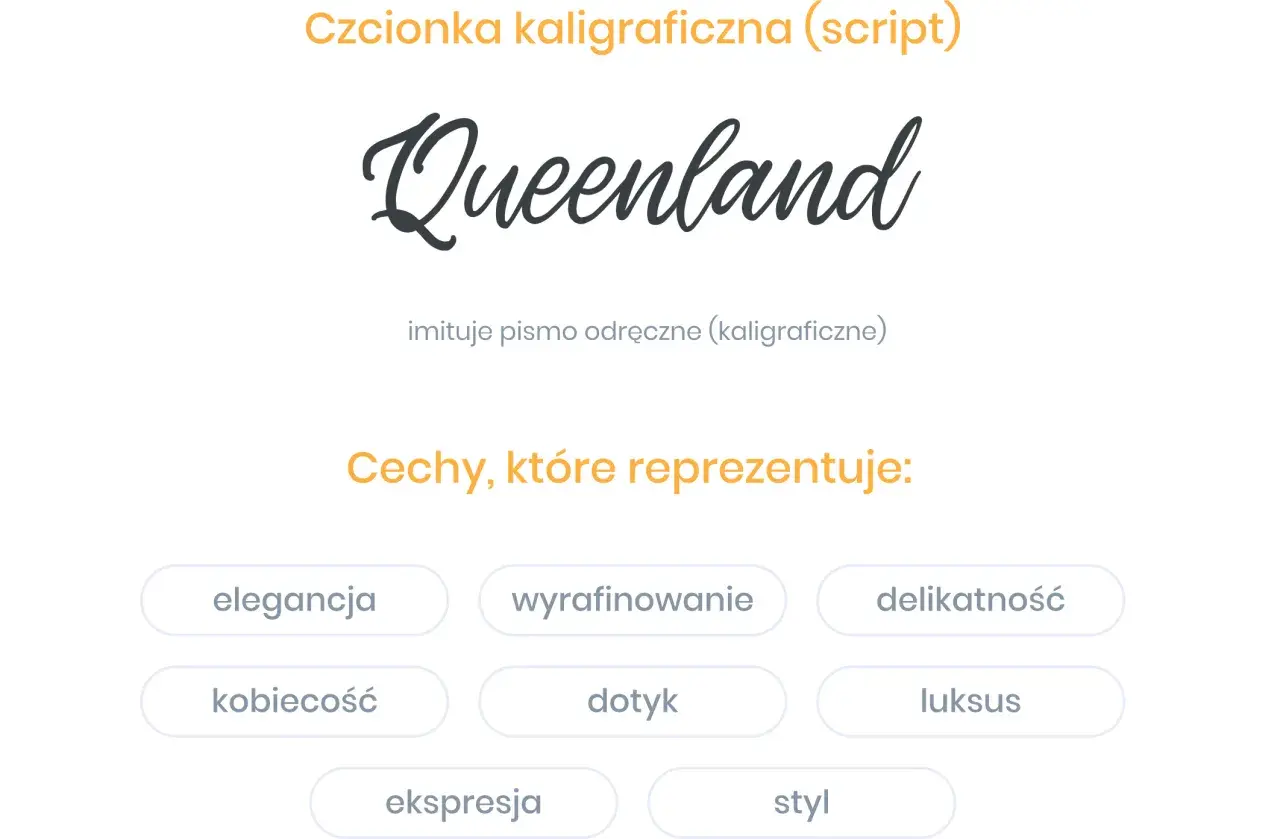
Dobry napis potrafi sprawić, że lokalna marka zostanie zapamiętana po jednym spojrzeniu. Czcionka ozdobna pomaga zbudować klimat reklamy, szyldu, menu czy posta w mediach społecznościowych, ale łatwo przesadzić z dekoracyjnością i stracić czytelność. Pokażę, jakie style warto rozważyć, gdzie sprawdzają się najlepiej i jak wybrać krój, który będzie efektowny także w praktycznym użyciu.
Ozdobny krój działa najlepiej wtedy, gdy wspiera komunikat marki
- Jedna dekoracyjna rodzina zwykle wystarczy w projekcie reklamowym.
- Polskie znaki trzeba sprawdzić przed rozpoczęciem składu.
- Nagłówki i krótkie hasła są lepszym miejscem dla ozdobnych liter niż długie akapity.
- Kontrast, rozmiar i odstępy decydują o czytelności bardziej niż sam styl fontu.
Co wyróżnia dekoracyjne kroje pisma
Font dekoracyjny ma przede wszystkim przyciągać uwagę i budować skojarzenia. Może przypominać pismo odręczne, dawny szyld, elegancką kaligrafię, plakat retro albo liternictwo inspirowane neonami. Nie traktuję go jednak jako zamiennika zwykłego fontu do całej treści. Jego siła polega na tym, że pojawia się w odpowiednim miejscu i w ograniczonej ilości.
W reklamie lokalnej typografia często zastępuje część obrazu. Nazwa kawiarni zapisana miękkim krojem sugeruje kameralność, a ciężkie litery w stylu vintage mogą pasować do burgerowni, barber shopu lub sklepu z odzieżą używaną. To nie jest wyłącznie kwestia estetyki. Krój pisma wpływa na to, czy odbiorca odbierze markę jako nowoczesną, elegancką, rzemieślniczą czy swobodną.
Najpopularniejsze style
- Kaligraficzne i skryptowe przypominają pismo odręczne, dlatego pasują do salonów kosmetycznych, pracowni florystycznych i marek ślubnych.
- Retro i vintage korzystają z grubych liter, dekoracyjnych szeryfów lub form inspirowanych dawnymi reklamami.
- Gotyckie przyciągają mocnym charakterem, ale wymagają ostrożności, bo w małym rozmiarze szybko tracą czytelność.
- Ręcznie rysowane dobrze wspierają komunikację marek lokalnych, rodzinnych i rzemieślniczych.
- Geometryczne display fonts są wyraziste, nowoczesne i często dobrze działają w krótkich hasłach promocyjnych.
Gdzie ozdobne litery sprawdzają się najlepiej
Najbezpieczniej używać ich w miejscach, w których odbiorca ma przeczytać kilka słów, a nie długi tekst. Dobrym zastosowaniem jest nazwa firmy, hasło kampanii, nagłówek oferty, etykieta produktu albo wyróżniona informacja na plakacie.
| Zastosowanie | Dobry wybór | Na co uważać |
|---|---|---|
| Szyld i kaseton | Grube litery retro, proste kroje dekoracyjne | Cienkie elementy i zbyt małe odstępy |
| Plakat lokalnej promocji | Wyrazisty nagłówek plus prosty font pomocniczy | Umieszczanie całej treści w jednym ozdobnym kroju |
| Menu i cennik | Dekoracyjna nazwa sekcji, czytelny tekst podstawowy | Długie opisy zapisane kaligrafią |
| Media społecznościowe | Duży napis, kontrastowe tło, mocny rytm kompozycji | Efekty, które znikają na ekranie telefonu |
| Logo | Indywidualnie dopracowane liternictwo | Gotowy font użyty bez korekty odstępów |
W praktyce najczęściej wybieram układ złożony z jednego kroju ozdobnego i jednego neutralnego. Pierwszy buduje charakter, drugi porządkuje informacje. Taki kontrast jest szczególnie ważny w reklamach usług, gdzie klient musi szybko odczytać nie tylko nazwę firmy, ale również telefon, adres, cenę albo termin promocji.
Jak wybrać styl dopasowany do marki
Nie zaczynam od przeglądania najładniejszych fontów. Najpierw określam, jakie emocje ma wywołać projekt i gdzie będzie oglądany. Ten sam dekoracyjny krój może wyglądać świetnie na zaproszeniu, ale zupełnie nie sprawdzić się na banerze przy ruchliwej ulicy.
Dopasuj formę do branży
Salon fryzjerski premium może skorzystać z eleganckiego pisma o delikatnych kontrastach, natomiast warsztat samochodowy potrzebuje cięższych, bardziej zdecydowanych liter. Dla piekarni lub cukierni dobrze działają kroje ręczne i retro, lecz przy komunikacji medycznej lepiej zachować umiar i postawić na spokój oraz łatwy odczyt.
Sprawdź słowo, którego naprawdę użyjesz
Podgląd alfabetu bywa mylący. Font może wyglądać świetnie na przykładowym haśle, a gorzej na nazwie zawierającej „ą”, „ę”, „ł” lub „ż”. Zawsze testuję pełną nazwę firmy, adres strony i najdłuższe słowo z projektu. Brak polskich znaków albo ich wyraźnie inny styl potrafi zepsuć nawet dobrze zaplanowaną identyfikację.
Oceń krój w docelowym rozmiarze
Ozdobne litery najlepiej wyglądają zwykle w większym rozmiarze. W grafice internetowej nagłówek może mieć orientacyjnie 32-72 px, a tekst pomocniczy powinien pozostać prosty i wyraźny. W materiałach drukowanych ważniejsze od konkretnej wartości punktowej jest wykonanie próbki w rzeczywistym rozmiarze, bo cienkie linie mogą zniknąć po wydruku lub przy oglądaniu z odległości.
Najlepszy wybór nie zawsze jest najbardziej dekoracyjny. Jeśli odbiorca nie odczyta nazwy firmy w ciągu kilku sekund, efektowna forma przestaje pomagać. Ja zaczynam od funkcji, miejsca publikacji i charakteru marki, a dopiero potem dobieram styl liter.
Dobrym testem jest pokazanie projektu kilku osobom bez dodatkowego komentarza. Jeśli potrafią odczytać hasło, wskazać ofertę i powiedzieć, jaki charakter ma firma, typografia spełnia swoje zadanie. Jeśli rozmawiają wyłącznie o tym, że napis jest „ładny”, ale nie pamiętają treści, czas uprościć projekt.